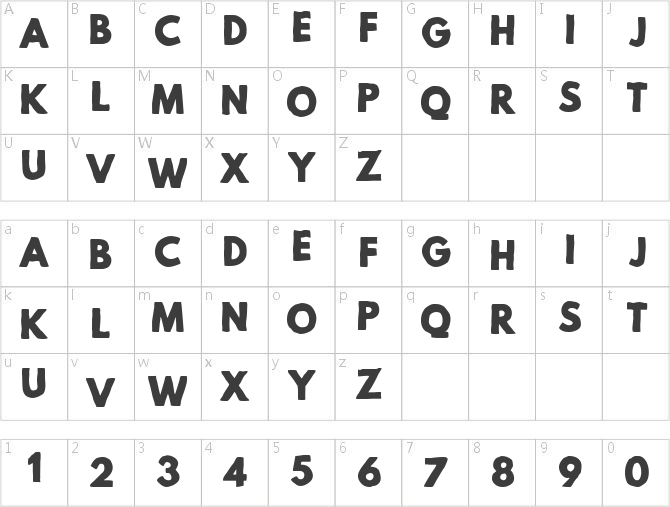
Mild Life Regular Personal Use 詳情頁
字體名稱: Mild Li
Mild Life Regular Personal Use
Mild Life Regular Personal Use字體字庫是一款讓人賞心悅目、百看不厭的英文字體,適合各類廣告和產(chǎn)品包裝設(shè)計應(yīng)用,字體大小0.03MB,格式為ttf字體,上傳用戶是瀨子,作者/版權(quán)方為未知